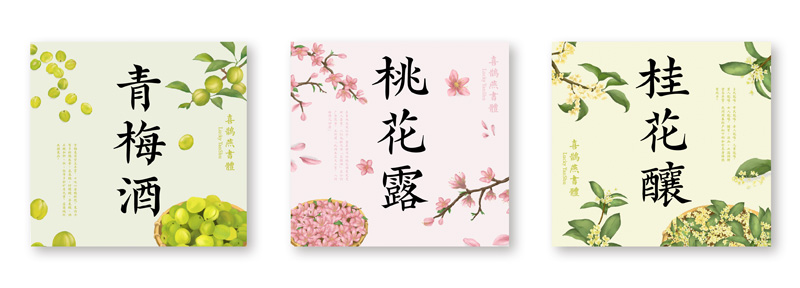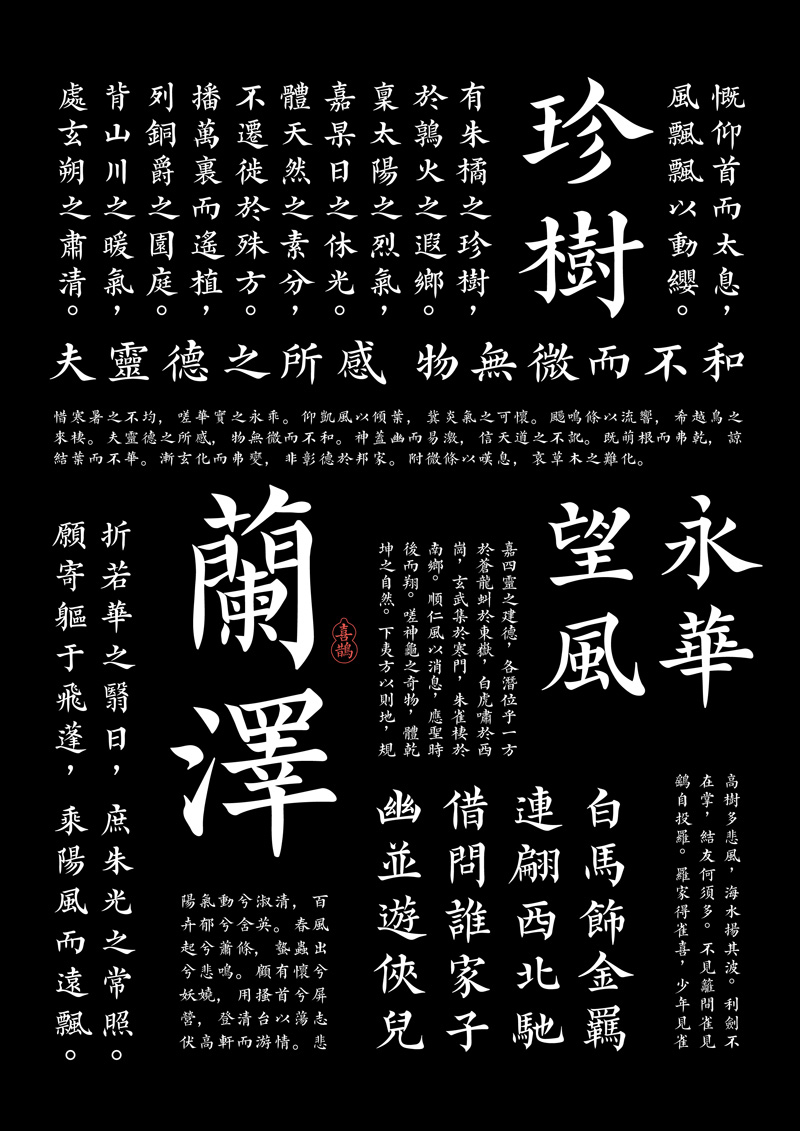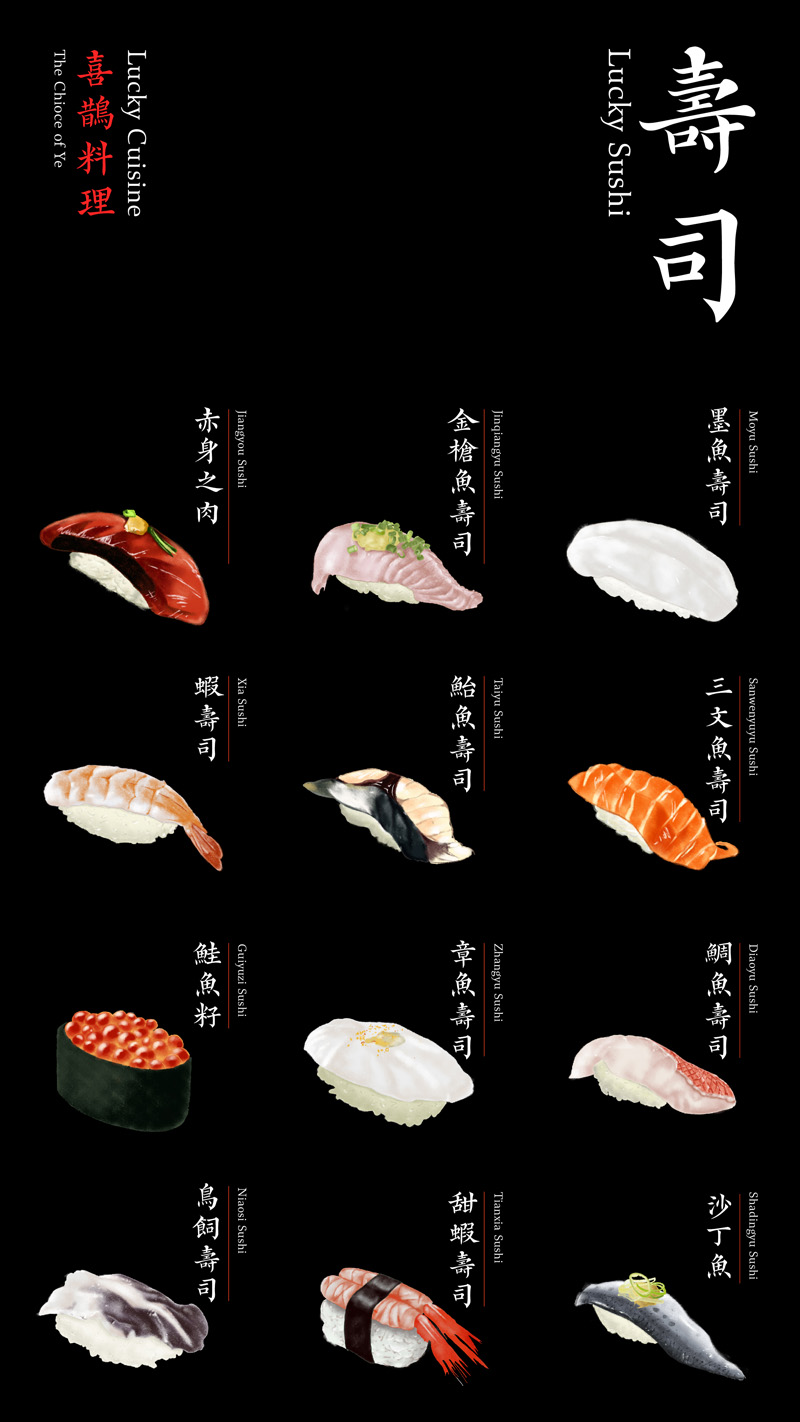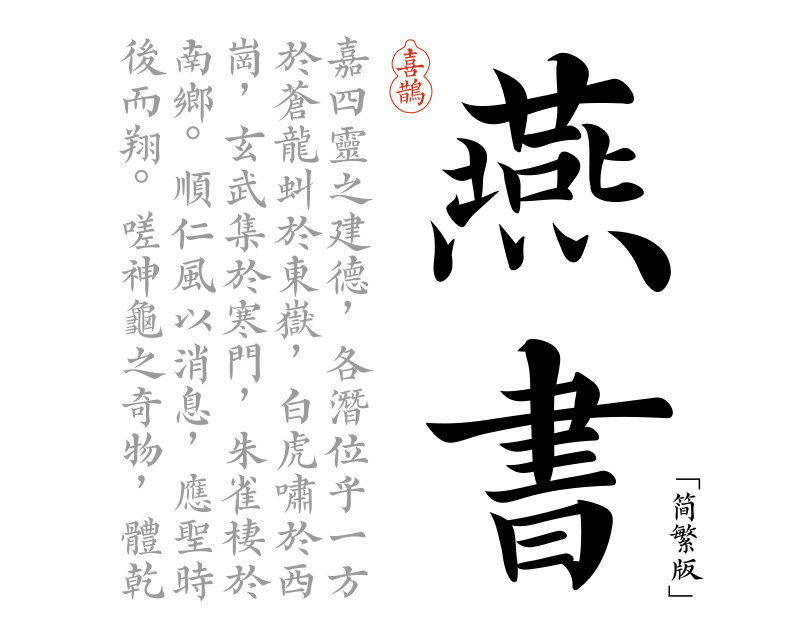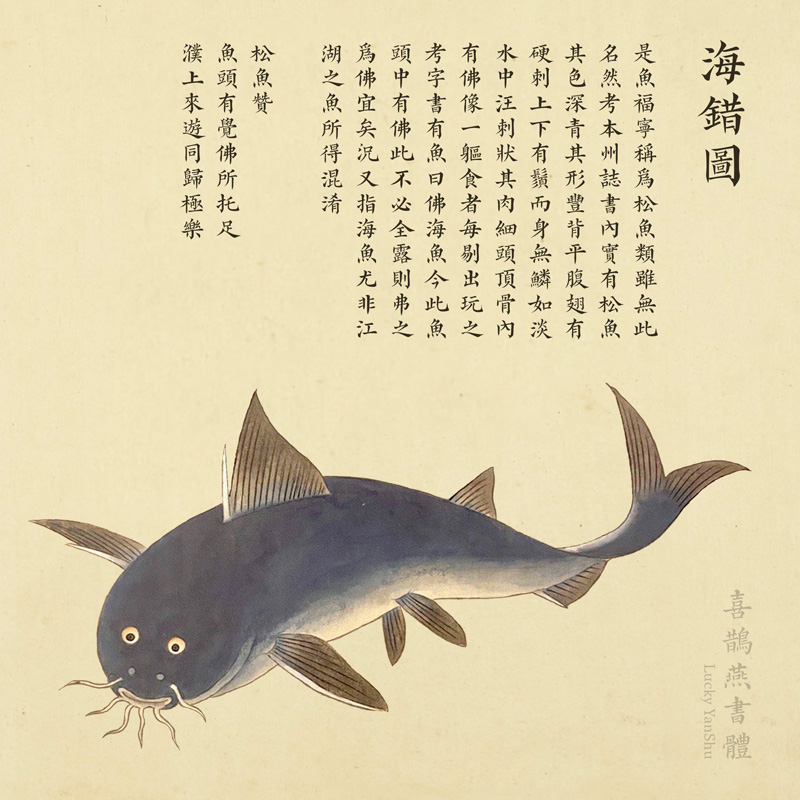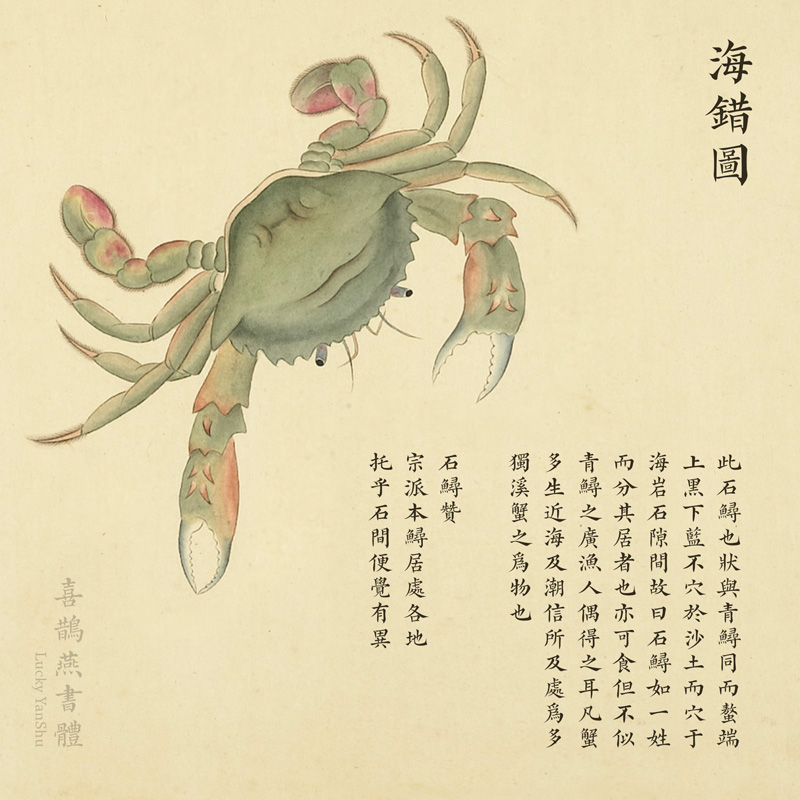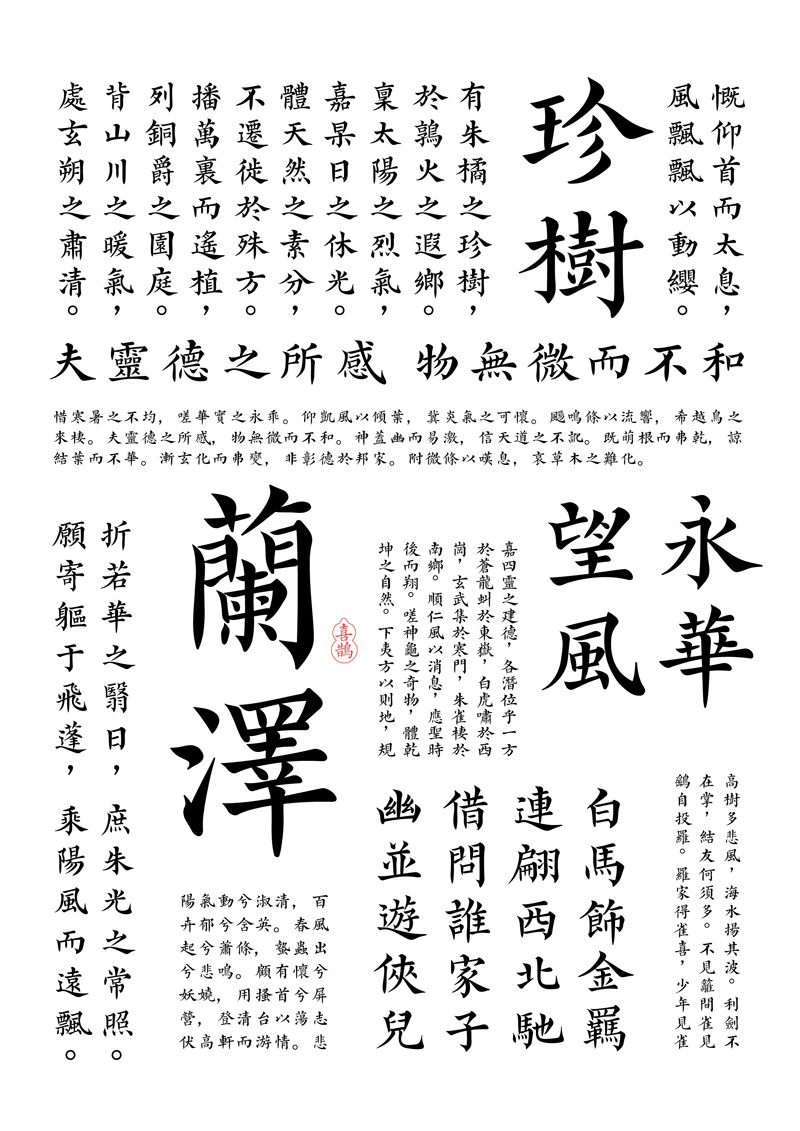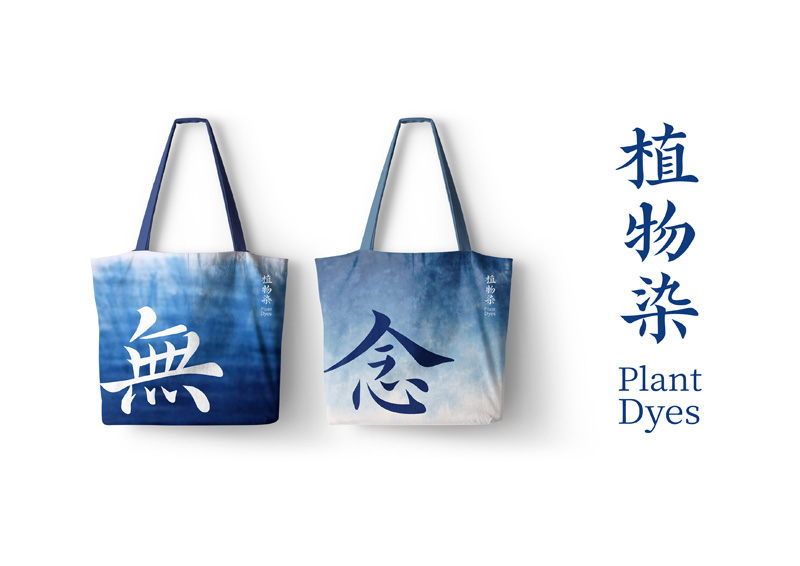
喜鹊造字新字 | 喜鹊燕书体-字迹清秀、曲线圆滑的中国风字体
字体介绍:此款楷体以清代五经精写古籍为蓝本。是一款利用数位板及iPad配合电脑软件设计制作而成的「电子书法字」。写时用笔松弛有度,笔画粗细过渡自然,意在保留楷体书写特征,且让字体拥有一种字迹清秀、曲线圆滑又舒展的美感。
适用场景:此字形非常适合用于各种中国风的正文或标题场景,比如中式餐饮,国潮国漫,国货文创,传统文化相关的影视衍生品等等。